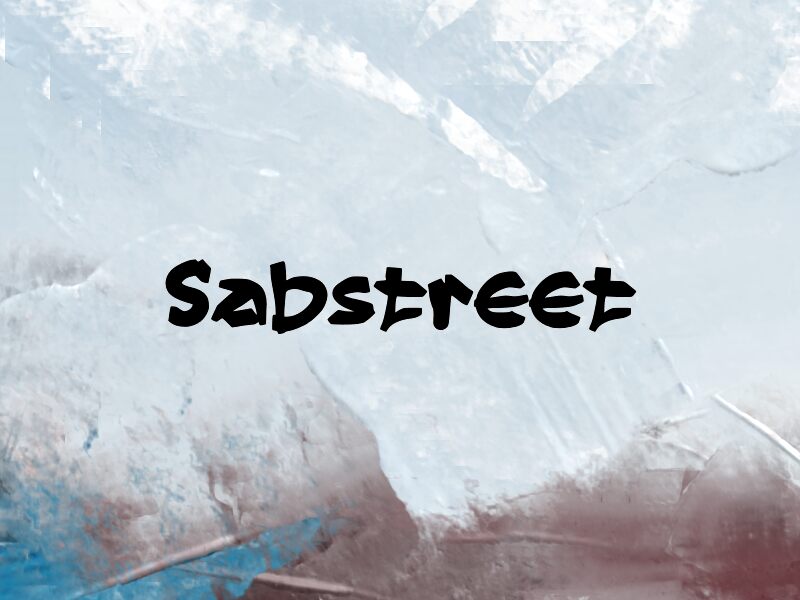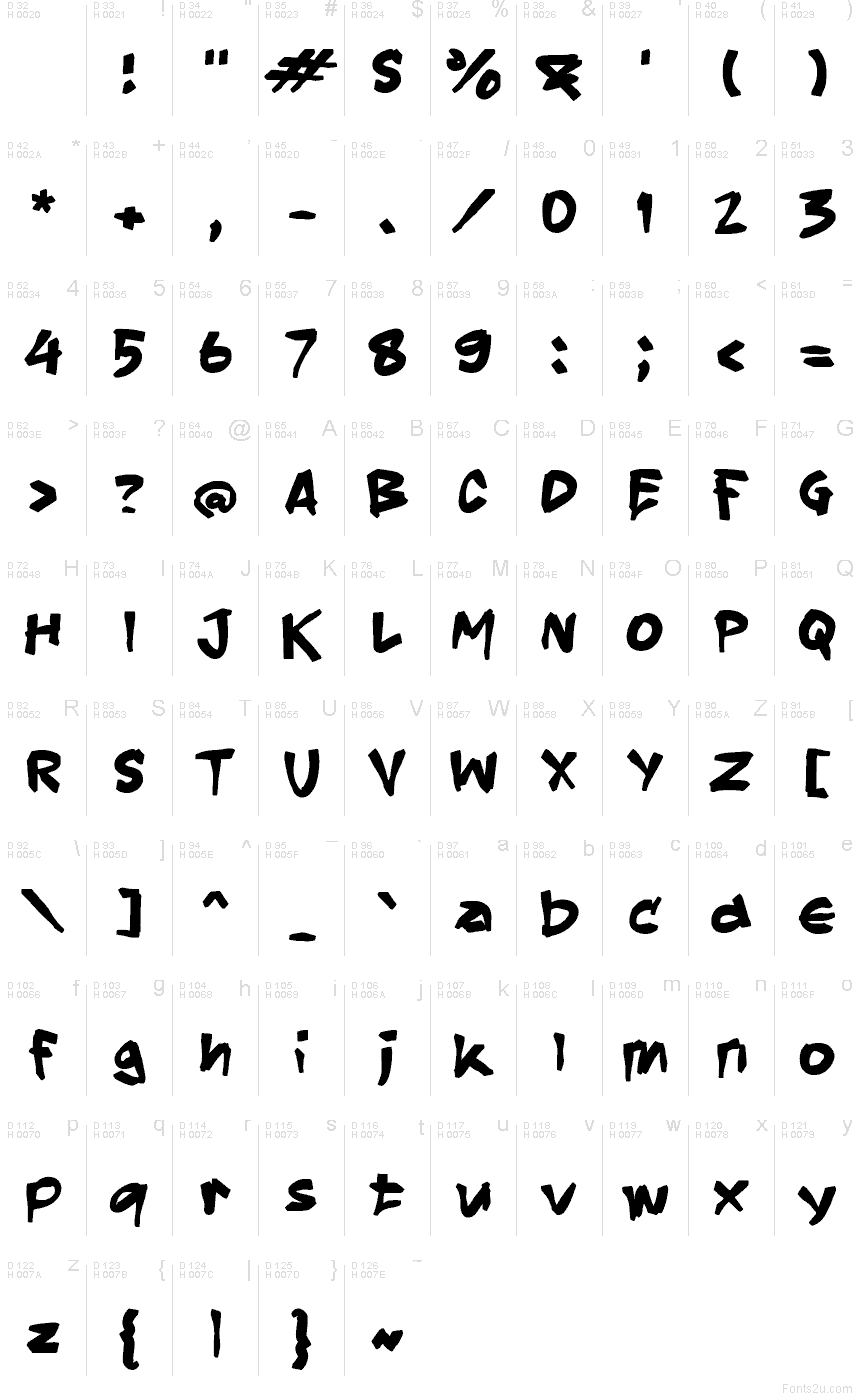
Sabstreet, da Wep, é uma fonte graffiti gratuita com um visual de rua bruto, cortado à mão. As letras parecem ao mesmo tempo pinceladas e talhadas – formas robustas e desiguais, curvas inchadas e pequenos cortes afiados conferem-lhe o ritmo áspero de um tag rápido na parede, em vez de letras polidas feitas com marcador.
Combina com cartazes, branding de skate e música, autocolantes, capas de zines, títulos e cabeçalhos curtos onde precise daquela energia urbana rebelde. Como fonte gratuita, a Sabstreet funciona melhor em apresentações breves, pois as suas silhuetas pesadas e arestas irregulares conferem a nomes simples e logótipos uma atitude solta e autêntica.
Sabstreet